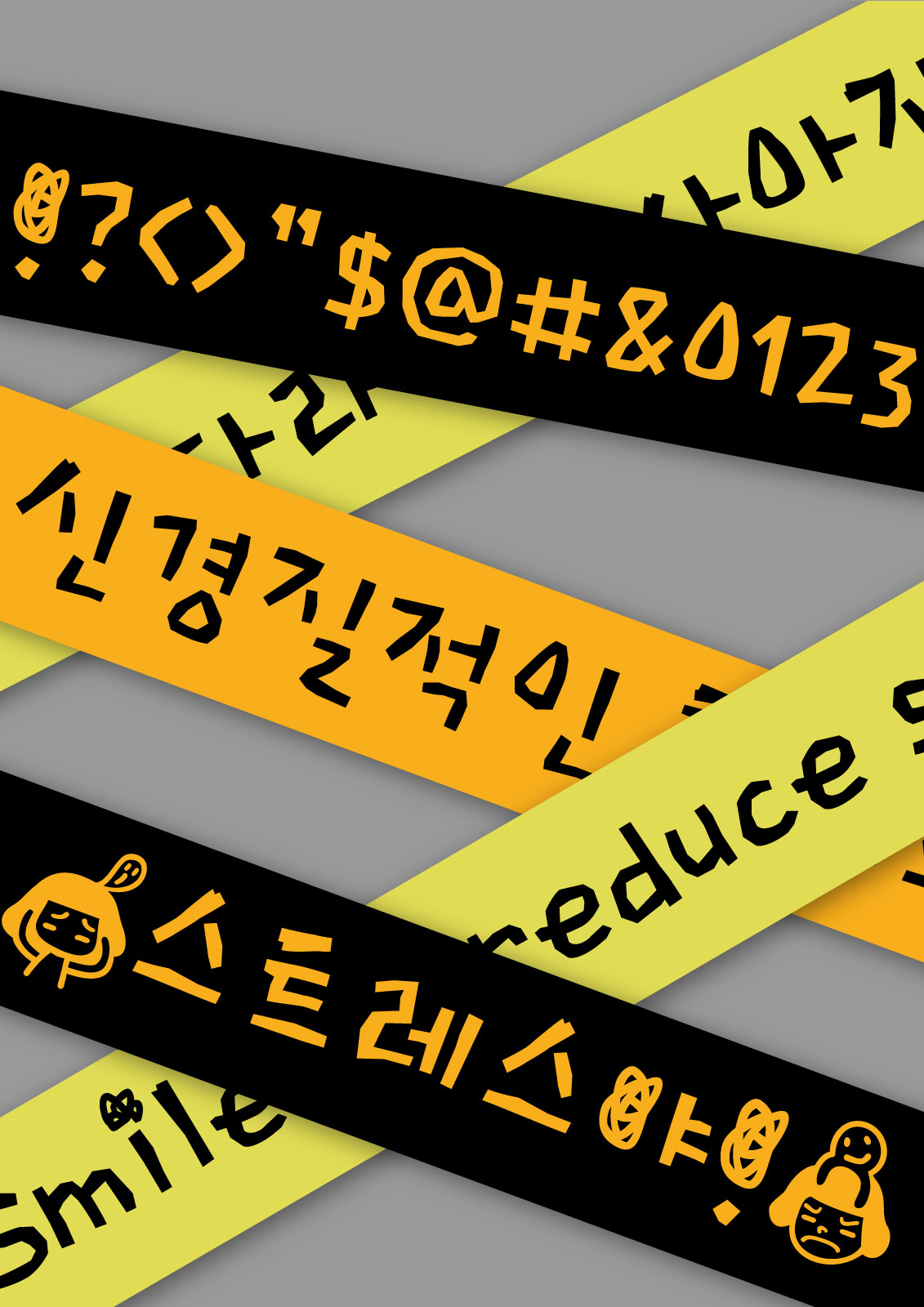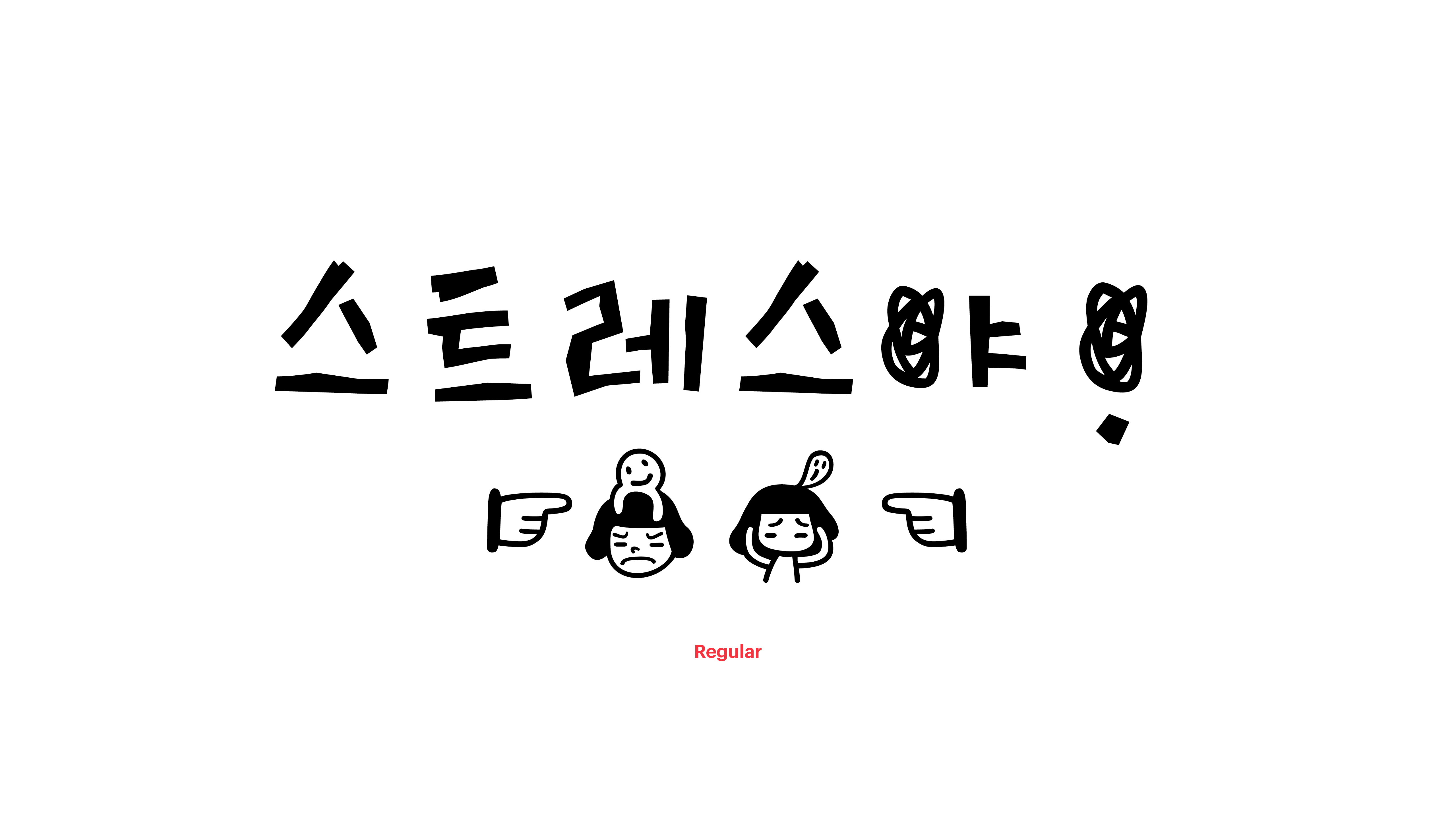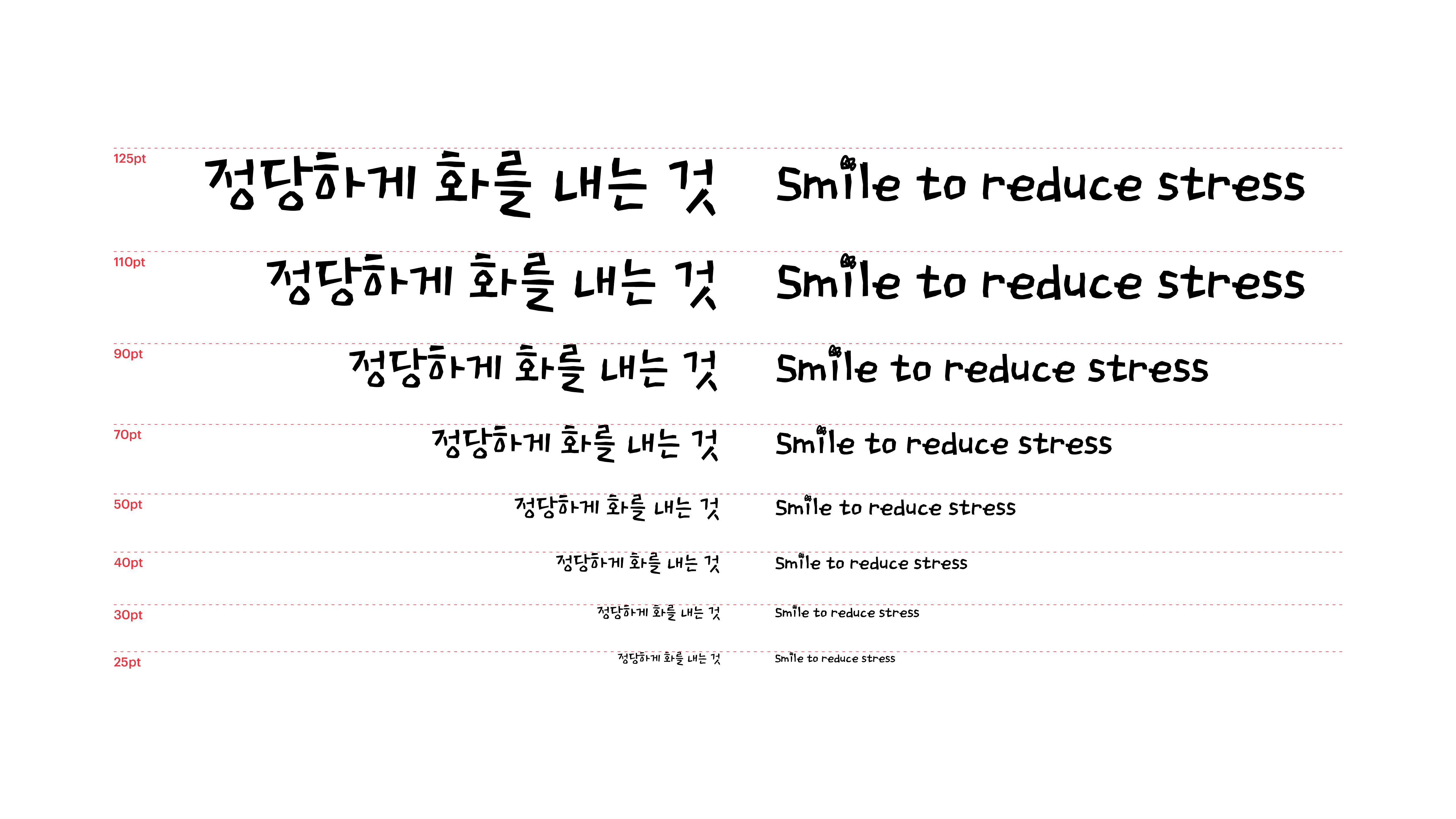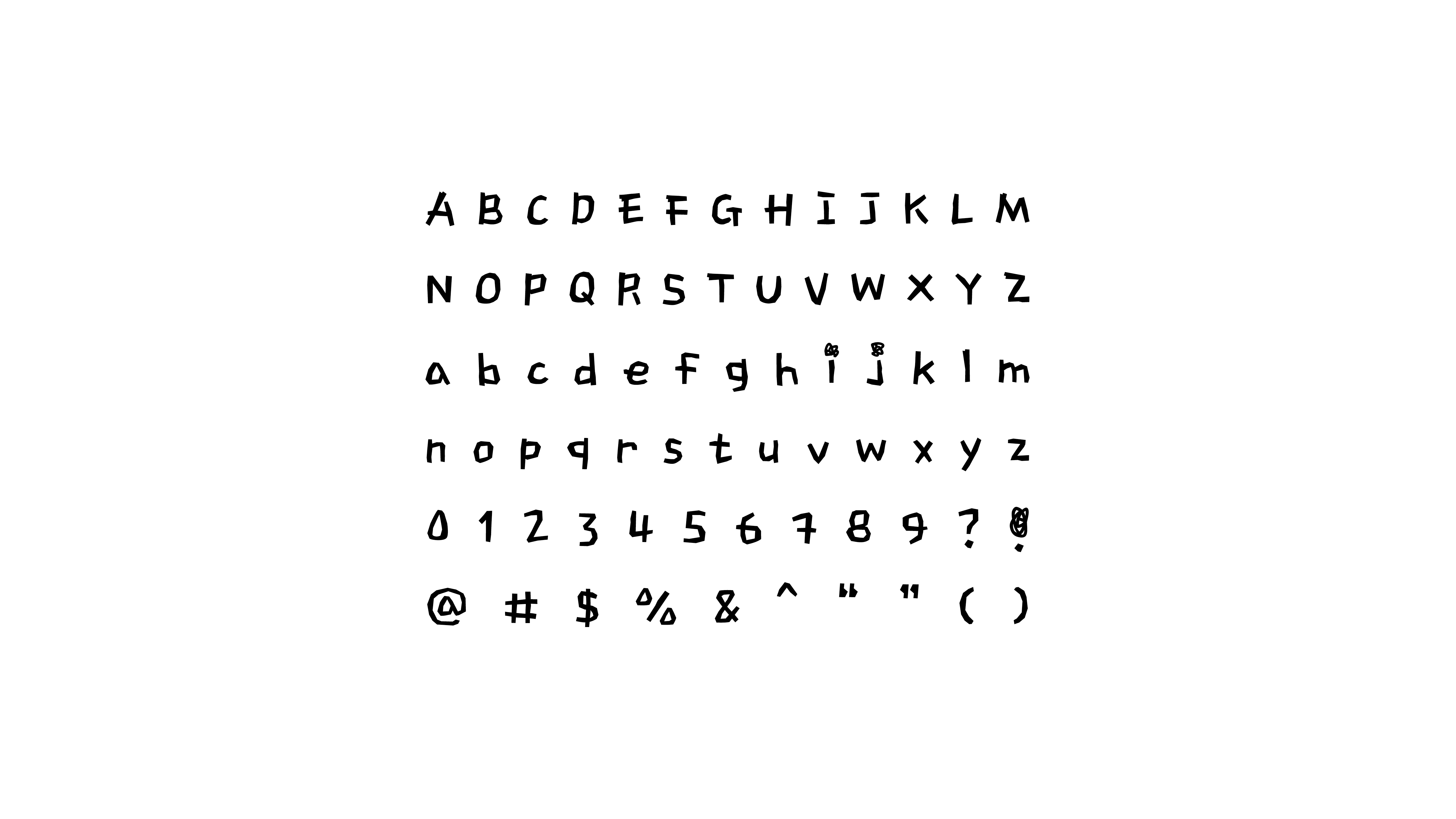
화가 날 때, 정당하게 화를 내는 것도 인생의 중요한 지혜랍니다. 하지만 막상 화를 내고 나면 어쩐지 멋쩍은 기분이 들어 자꾸만 망설이게 되지요. 혹시 신경질적 형태와 질감이 살아 있는 스트레스야체의 도움을 받아 보신 적 있나요? “양말 아무 데나 벗어 놓지 말랬지?”, “혼자서 다 먹다니, 목숨이 두 개냐?” 어때요? 꽤 현명한 절충안이죠? 하지만 그렇다고 너무 자주 써먹으면 안 돼요. 효과를 극대화하기 위해서 적재적소에만 사용하는 센스를 잊지 마세요!
Yoon 스트레스야